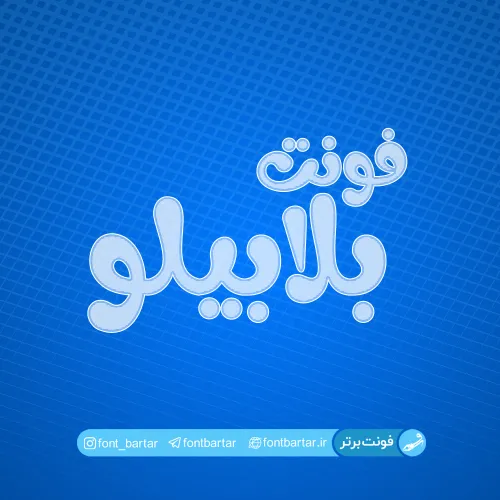
فونت فارسی بلابیلو
در این مطلب از سایت فونت برتر شاهد ، فونت زیبا و جذاب ” بلابیلو نسخه فارسی سازی شده ” هستید ، فونت فارسی بلابیلو پس از مدت نه چندان زیادی که از طراحی آن میگذرد به سبب طرح دل نشین آن جایگاه ویژه ای پیدا کرده است،نسخه جدید فونت ” بلابیلو ” را آقای ” هاشم شهرزاد ” ویرایش کرده است، در این نسخه شاهد تغییرات چشم گیری هستیم.
تغیرات ایجاد شده در نسخه جدید فونت بلابیلو:
- اضافه شدن حرف ” گ “
- اضافه شدن حرف ” چ “
- اضافه شدن حرف ” پ “
- اضافه شدن حرف ” ژ “